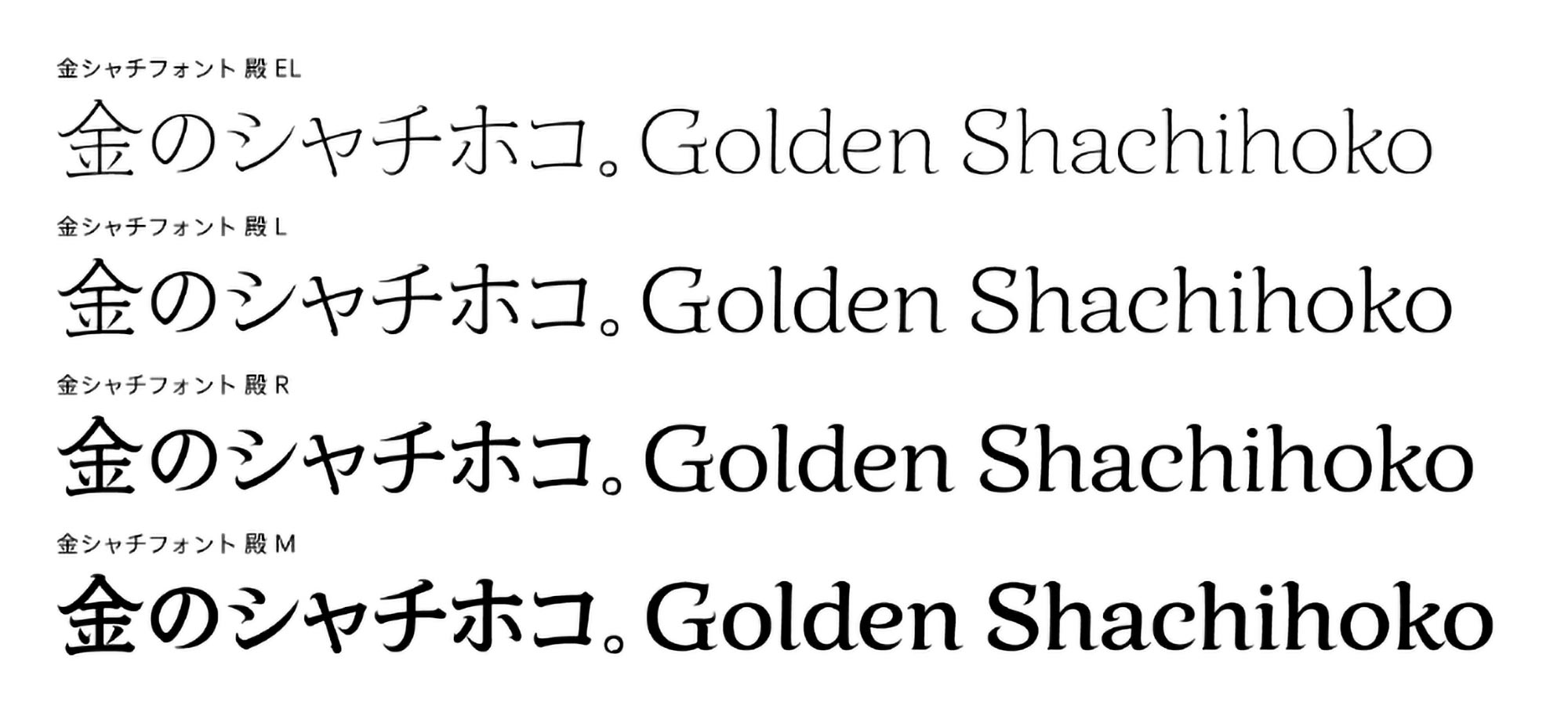
タイププロジェクト、「金シャチフォント 殿」を8ウエイトに展開
EL、L、R、Mの4ウエイトを新たに追加
金シャチフォントは、名古屋文化の象徴を反映したフォントで、都市フォントプロジェクトとして開発しました。地域特有の文化資源を書体デザインに活用する。これはタイププロジェクトが提唱している都市フォント構想を貫く基本的な考えかたです。都市フォント構想は、都市が持っている個性や魅力をフォントのデザインに取り入れることで、都市らしさを具現化するための構想です。
堂々たる殿様ぶりを感じさせる筆文字系の金シャチフォント 殿は、尾張徳川家の合印でもある名古屋の市章「丸八」の筆法をベースにしています。先にリリースした肉太で力強いDB (デミボールド)、B (ボールド)、H (ヘヴィ)、Blk (ブラック)の4ウエイトに加え、細さのなかにも筆文字独特の粘り強さをもつEL (エクストラライト)、L (ライト)、R (レギュラー)、M (ミディアム)の4ウエイトを追加しました。
タイププロジェクトの代表取締役 鈴木 功は、「金シャチフォント 殿のウエイトはこれで『八』となり、実用性を向上させるとともに、末広がりで縁起の良い数にまとまったことを喜ばしく思います。ユニークな漢字と仮名のデザインを支える欧文の出来ばえも出色だと自負しています。高品質な筆書系欧文フォントとしてさまざまな場面でご活用いただけます。これまでの江戸文字とはひと味ちがう金シャチフォント 殿シリーズをぜひお試しください」と述べています。
江戸文字系フォントが使用される場面のほとんどはディスプレイ用途にかぎられていましたが、金シャチフォント 殿のEL、L、R、Mの4ウエイトの登場によって、大小さまざまな見出しからテキストまで使用シーンが大幅に広がります。
ウエイト:EL (エクストラライト)、L (ライト)、R (レギュラー)、M (ミディアム)